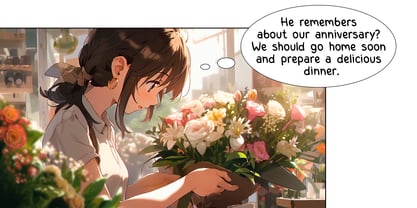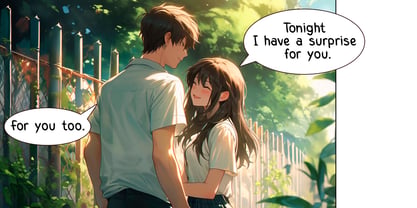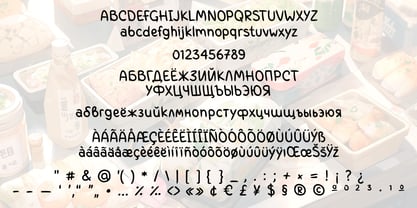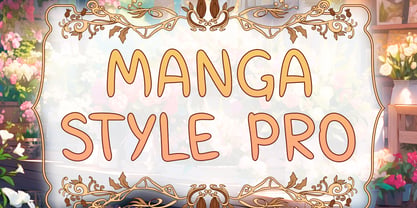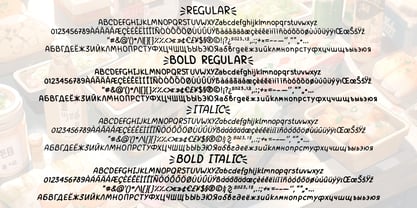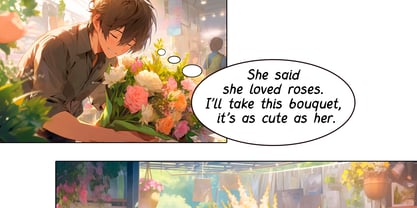
Manga Style Pro
por AVFontoria
La familia tipográfica Manga Style Pro fue diseñada por Alisa Voloshina y publicada por AVFontoria. Manga Style Pro contiene 4 estilos y opciones de paquete familiar. Más información sobre esta familia
Font for comics and mangas. Supports extended Cyrillic and Latin characters. Has four styles.
Diseñadores: Alisa Voloshina
Fundición: AVFontoria